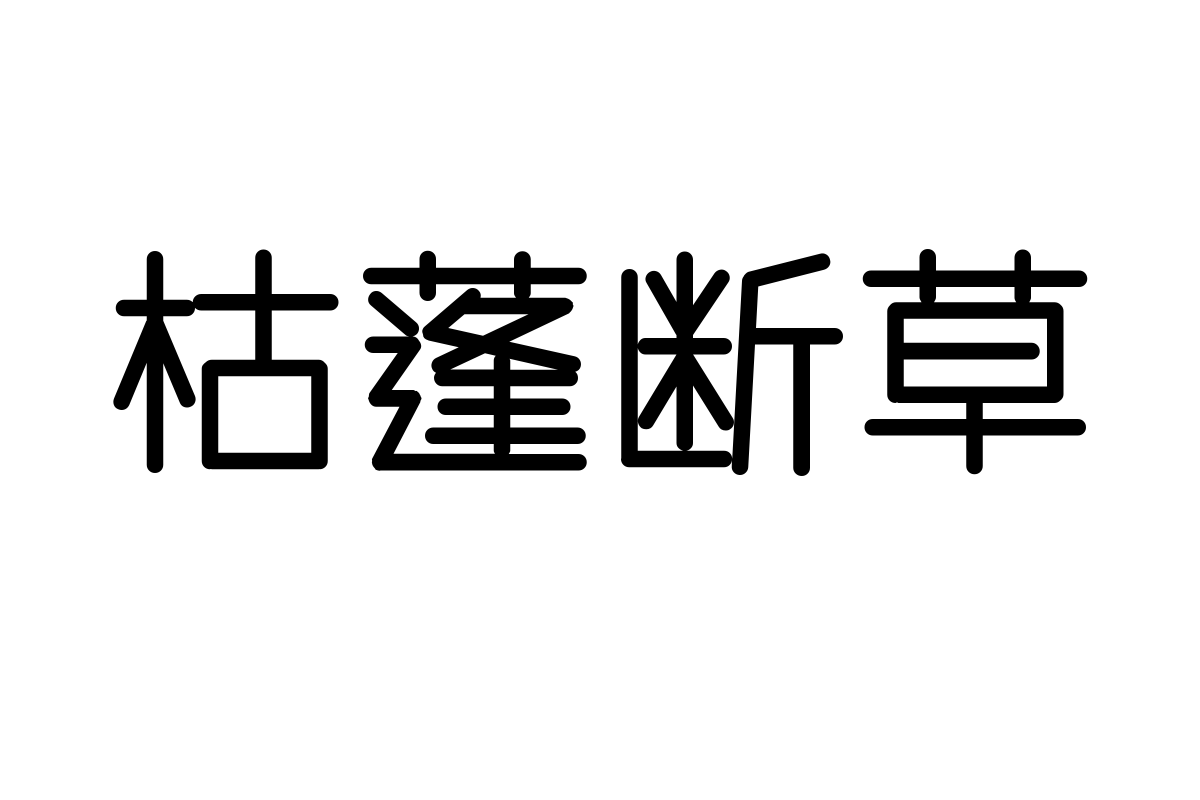
汉仪良品线粗简是一款简洁而现代的中文字体,适用于各种设计项目。这款字体以其清晰的线条和优雅的字形而受到广泛欢迎。
特点:
1. 简洁性:汉仪良品线粗简的字形简单明了,易于阅读和理解。
2. 易读性:该字体的笔画粗细适中,使得文字在视觉上具有很好的可读性。
3. 现代感:这款字体的设计现代而时尚,适合用于商业、科技、广告等领域。
4. 适应性强:无论是标题、正文还是小标题,汉仪良品线粗简都能很好地适应不同的设计需求。
5. 兼容性好:该字体支持多种字符集,包括汉字、英文等,能够满足不同语言的需求。
总之,汉仪良品线粗简是一款优秀的中文字体,适用于需要清晰、易读且现代感强的各类设计项目。